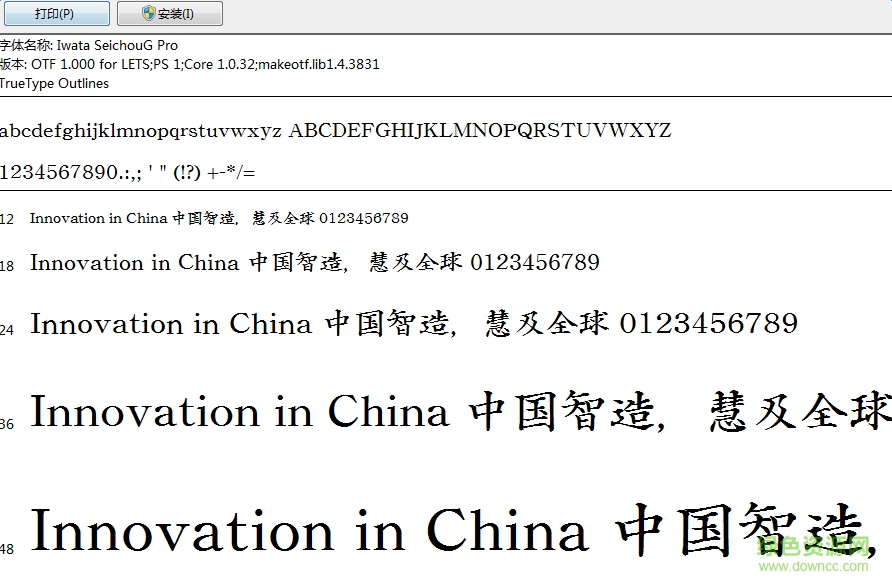
弘道軒清朝體現(xiàn)代版字體是一款弘道軒清朝體的現(xiàn)代復(fù)刻版,保留了原字體的個(gè)性,又新增了現(xiàn)代流行字體的風(fēng)格,非常潮流時(shí)尚,該字體可以廣泛應(yīng)用于橫幅標(biāo)語(yǔ)、美術(shù)設(shè)計(jì)、宣傳海報(bào)、ppt、影視制作以及任何使用文字的領(lǐng)域,有需要的朋友可以免費(fèi)下載收藏。